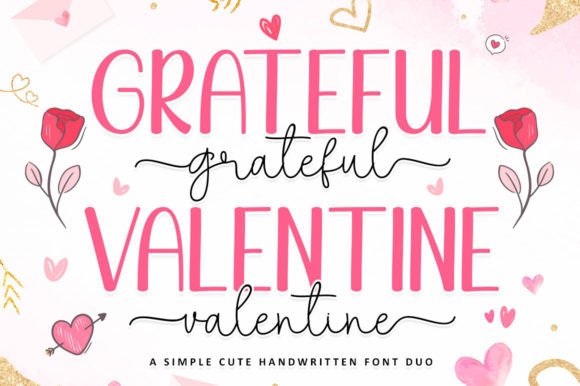
Grateful Valentine
Grateful Valentine – A Fonte Script que Transforma Cada Projeto
Se você ainda não conhece a Grateful Valentine Font Duo, está perdendo a oportunidade de elevar seus trabalhos criativos a outro nível. Desenvolvida à mão em estilo freestyle, esta fonte script combina elegância romântica com ótima legibilidade, tornando‑a a escolha ideal para designers, artesãos e pequenos negócios que buscam um toque pessoal e sofisticado.
Por que a Grateful Valentine se destaca?
- Versatilidade incomparável: perfeita para logotipos, convites de casamento, cabeçalhos, camisetas, papel timbrado, sinalização, rótulos, newsletters, pôsteres e badges.
- Glyphs e ligaduras avançadas: como a fonte é codificada em PUA (Private Use Area), você tem acesso fácil a centenas de glifos especiais e ligaduras que dão fluidez ao texto.
- Qualidade artesanal: cada traço foi desenhado à mão, garantindo um visual único e autêntico que nenhuma fonte “genérica” oferece.
Aplicações práticas que brilham com Grateful Valentine
Imagine um convite de casamento onde o nome dos noivos aparece em uma caligrafia delicada, ou uma camiseta com uma frase inspiradora que flui como se fosse escrita à mão. A Grateful Valentine entrega exatamente isso: charme, personalidade e profissionalismo em cada caractere.
Para quem busca uma tipografia que una estilo artesanal e funcionalidade moderna, a Grateful Valentine Font Duo é a escolha certa. Seja para projetos pessoais ou comerciais, ela garante um visual elegante e memorável, além de oferecer um conjunto completo de glifos e ligaduras que facilitam a criação de designs sofisticados.